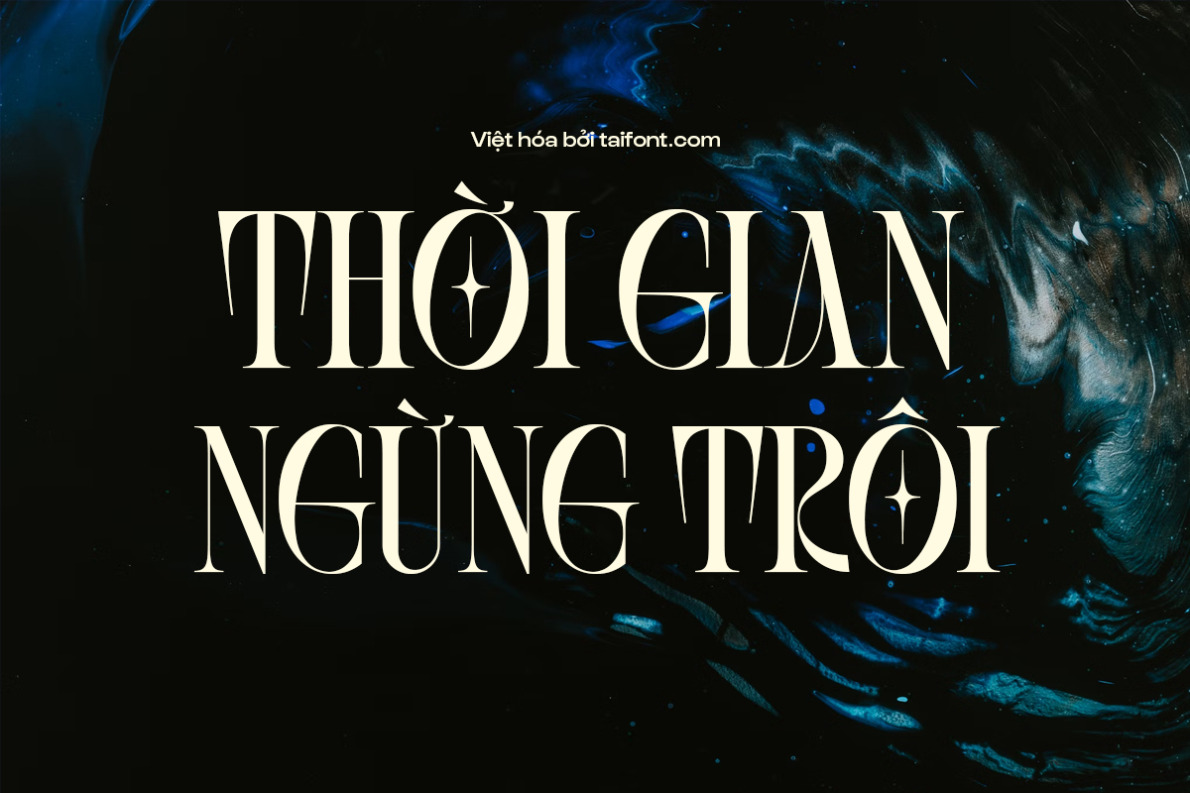
Giới thiệu về Font TF Boxroom Việt hóa
TF Boxroom Việt hóa là một font chữ có chân (serif) nổi bật với thiết kế thanh lịch, tinh tế và đầy sang trọng. Font này mang đến vẻ đẹp cổ điển kết hợp hiện đại, toát lên phong thái quý phái, đẳng cấp và sự cuốn hút đặc biệt, lý tưởng cho mọi ấn phẩm cần sự tinh xảo và độc đáo.
Với sự tinh xảo trong từng ký tự và tính thẩm mỹ vượt trội, Boxroom là lựa chọn hoàn hảo cho các thiết kế muốn truyền tải sự sang trọng và phong cách, đặc biệt là trong các lĩnh vực:
- Thiết kế thời trang và tạp chí: Hoàn hảo cho các thương hiệu thời trang cao cấp, từ logo, nhãn mác sản phẩm, đến các lookbook và chiến dịch quảng bá bộ sưu tập. Font này giúp truyền tải vẻ đẹp thanh lịch, đẳng cấp và độc đáo của trang phục, nâng tầm giá trị thương hiệu. Đặc biệt, nó lý tưởng để sử dụng cho các tiêu đề chính, lời dẫn, hoặc nội dung bài viết trong các tạp chí về thời trang, làm đẹp, lối sống cao cấp. Nét chữ có chân của Boxroom giúp tăng tính trang trọng và dễ đọc, đồng thời tạo cảm giác cao cấp, thu hút độc giả.
- Thiết kế thiệp cưới: Lý tưởng để viết tên cô dâu chú rể, lời mời cưới, hoặc các thông tin chi tiết trên thiệp cưới, menu tiệc, bảng tên khách mời. Những nét chữ tinh tế, sang trọng sẽ biến mỗi tấm thiệp thành một tác phẩm nghệ thuật, mang đậm dấu ấn cá nhân và sự lãng mạn, trang trọng cho ngày trọng đại.
- Thiết kế nhận diện thương hiệu: Phù hợp cho logo, tagline hoặc bộ nhận diện thương hiệu của các công ty, doanh nghiệp muốn truyền tải sự tinh tế, uy tín và sự thanh lịch. Boxroom giúp xây dựng một hình ảnh thương hiệu vững chắc và dễ nhận diện.
Với TF Boxroom Việt hóa, bạn có thể dễ dàng thổi hồn tinh tế, sang trọng và vẻ đẹp hoàn hảo vào các thiết kế, tạo ra những sản phẩm không chỉ đẹp mắt mà còn đầy cảm xúc và sức hút đặc biệt.
Font Việt hóa TF Boxroom
Dấu â, ă, huyền, sắc, ngã được kế thừa từ dấu font Beautique Display. Còn dấu hỏi, ư thì tự vẽ